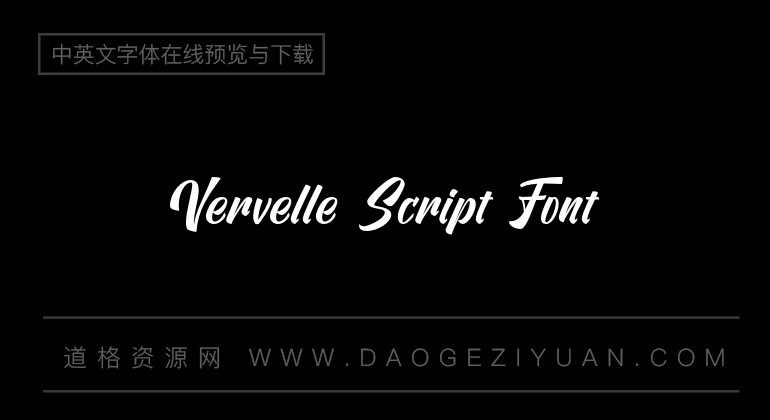
Vervelle Script Font
Vervelle Script Font 是一种优雅的手写字体,其风格具有精美的笔画和优美的连笔。该字体适用于许多不同的设计项目,包括卡片、海报、标志、书籍封面等。 Vervelle Script Font 字体中的每个字母都具有独特的形状和风格,这使得它非常适合那些寻求突出品牌个性和风格的设计师。此外,该字体的大小和颜色可以轻松修改,以满足各种设计需求。 总之,Vervelle Script Font 字体是一种非常优雅和多功能的字体,适用于各种设计项目和风格。
Vervelle Script Font是一款非常不错的手写艺术字体,具有很好的视觉感,适合于文化类的宣传设计、商业类品牌的广告和产品包装设计以及个性化文字排版等较多场景。